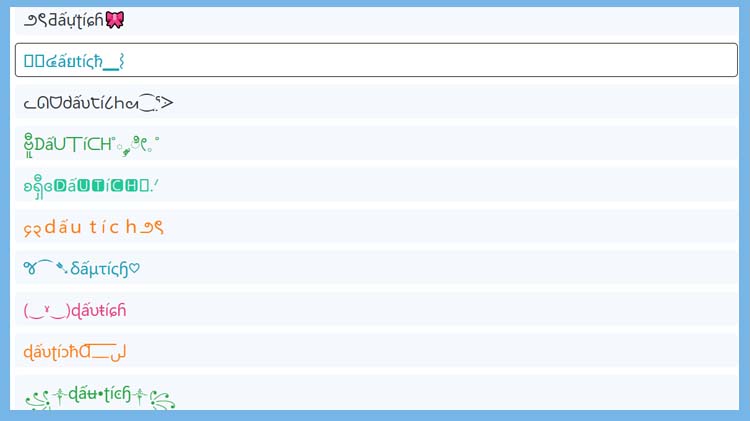
Khám phá những kí tự đặc biệt dấu tích thông dụng, có màu sắc, đẹp
Dấu tích (✓, ✅), còn gọi là check mark, là ký tự đặc biệt dùng để biểu thị sự hoàn thành, xác nhận, lựa chọn, đồng ý hoặc tính chính xác). Biểu tượng này đóng vai trò quan trọng trong nhiều hệ thống thông tin để xác nhận trạng thái "đã xong" hoặc "đã chọn".
Trong bài viết dưới đây, Mobifonts sẽ cùng các bạn khám phá các kí tự đặc biệt dấu tích có màu sắc và đẹp nhất hiện nay. Bên cạnh đó, chúng tôi sẽ giải đáp chi tiết một số câu hỏi thường gặp, giúp bạn có thêm kiến thức khi sử dụng kí tự này.
Kí tự đặc biệt dấu tích không chỉ là một biểu tượng đơn giản mà còn mang ý nghĩa sâu sắc. Loại kí tự này được sử dụng để chỉ sự hoàn thành, đồng ý hoặc đánh dấu một lựa chọn nào đó. Theo Unicode Consortium, kí tự dấu tích (Check Mark) có mã Unicode là U+2713. Dưới đây là gợi ý một số kí hiệu dấu tích thông dụng dành cho bạn:
√͎
√͓̽
√̾
√̳
√̲
√̷
√̴
✓
≋✓≋
✓
〜✓〜
░✓░
⟦✓⟧
꜍✓꜉
Dấu tích không chỉ sử dụng trong các văn bản thông thường mà còn có thể được điều chỉnh về màu sắc như xanh dương xanh lá,... để tạo điểm nhấn. Dưới đây là những kí tự dấu tích có màu sắc, mang lại nhiều cảm xúc và ý nghĩa khác nhau:
Khi muốn kí tự dấu tick trở nên đặc biệt và đẹp mắt hơn, bạn có thể thử các biến thể sáng tạo. Kí tự dấu tích đẹp khi được kết hợp với các hình ảnh hoặc kiểu dáng khác sẽ tạo nên sự hấp dẫn cho nội dung của bạn. Sau đây là một vài gợi ý về kí tự dấu tích đẹp, tạo điểm nhấn cho câu chuyện hoặc thông điệp bạn muốn truyền tải:
꧁༒ɖấʉ•ʈíͼɧ༒꧂
ɖấυʈíɔħⱭ͞ ̶͞ ̶͞ ̶͞ لں͞
(‿ˠ‿)ɖấυŧíɕɦ
જ⁀➴δấμτíςɧ♡
၄၃dấutích౨ৎ
ᓚᘏᗢძấυ੮í८Һᘛ⁐̤ᕐᐷ
౨ৎƋấựʈíɕɦ🎀
Trong các cộng đồng yêu thích kí tự đặc biệt, nhiều người dùng thường đặt ra các thắc mắc như có thể tạo kí hiệu dấu tích theo ý muốn không, có thể sử dụng kí tự này trong các nền tảng mạng xã hội không hay làm thế nào để tạo chúng trong văn bản. Tất cả các câu hỏi này sẽ được Mobifonts giải đáp chi tiết ngay sau đây.
Hoàn toàn có thể sử dụng kí tự dấu tích trong các ứng dụng mạng xã hội như Facebook, TikTok, Zalo, Instagram,... Đây là một ký tự thuộc bảng mã Unicode, vì vậy hầu hết các nền tảng và thiết bị hiện nay đều hỗ trợ hiển thị đúng. Người dùng chỉ cần sao chép ký hiệu dấu tích như ✓, ✔ hoặc ✅, sau đó dán vào bài đăng, bình luận hoặc mô tả.